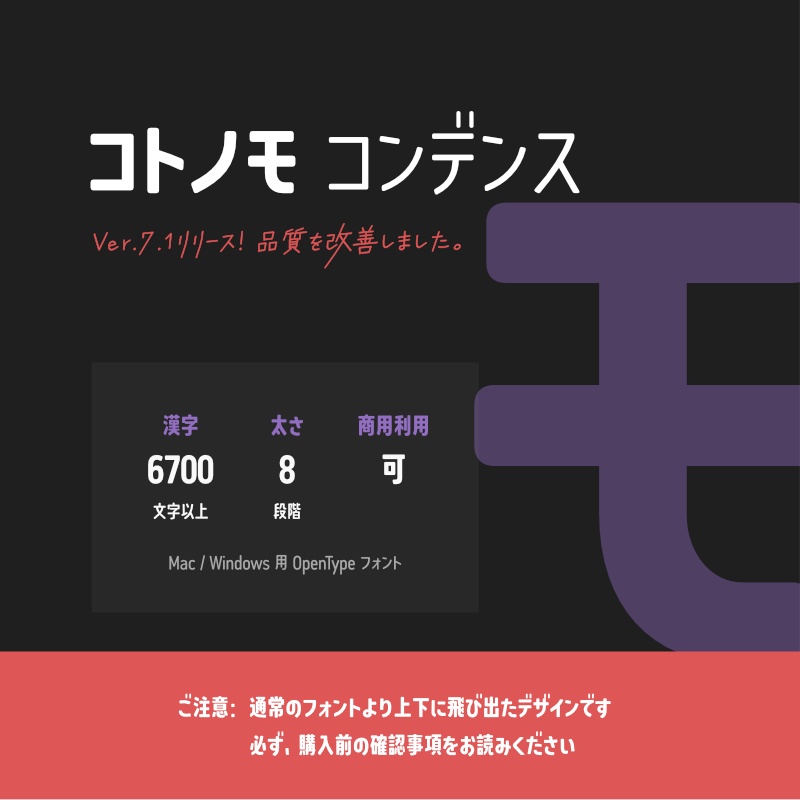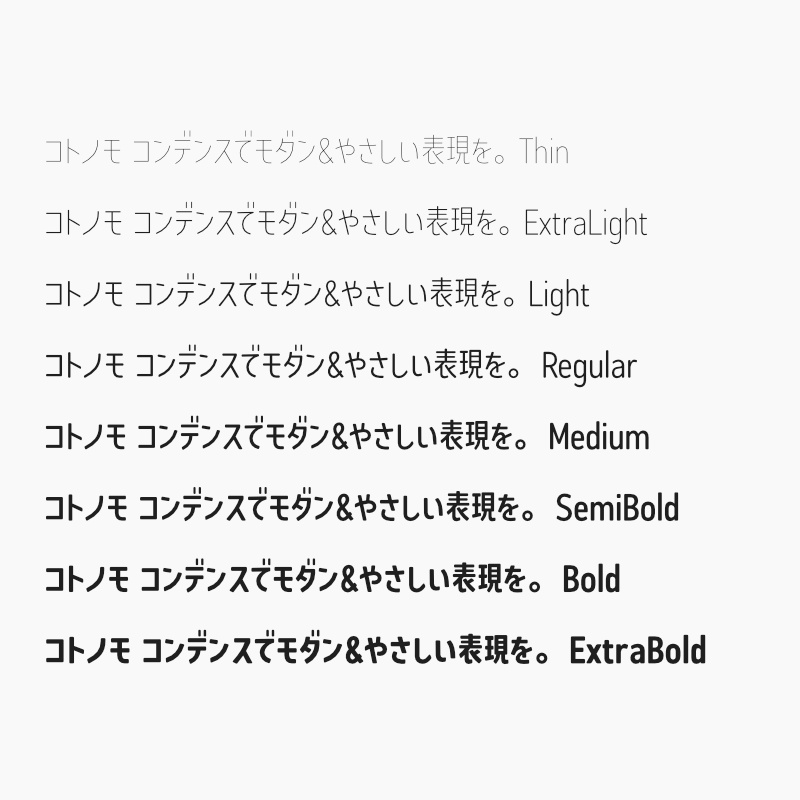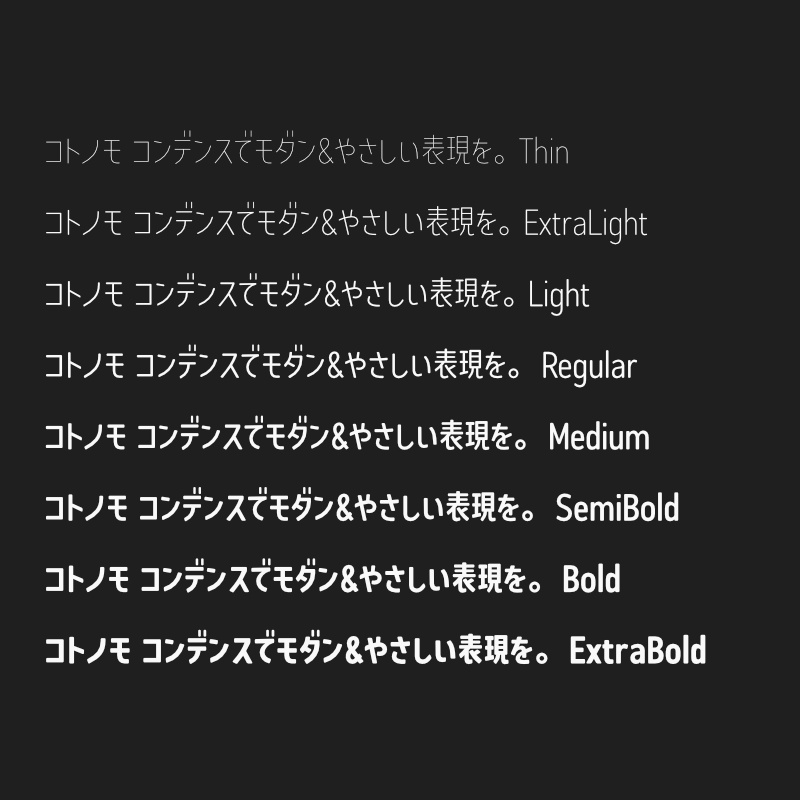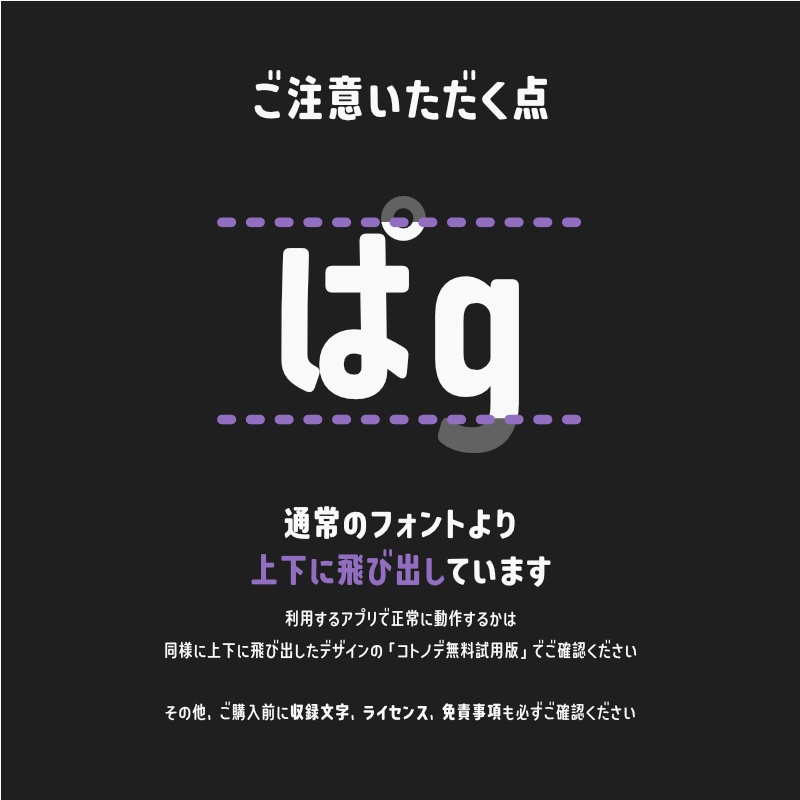
「コトノモ コンデンス」フォント(漢字あり) ~縦長で角丸のかわいい丸ゴシック体~
2024/09/30 ver.3.410 リリース。 2025/01/14 ver.3.600 リリース。一部の文字の表示崩れを修正しました。 2025/03/25 ver.4.105 リリース。濁点の位置を微調整しました。いくつかの文字のデザインを微調整しました。 2025/09/08 ver.4.106 リリース。一部カタカナのデザインを微調整しました。「以」「似」などを画数に忠実なデザインに変更しました。「篝」をJIS2004字形に変更しました。 2026/09/07 ver.7.103 リリース。「ð」「冕」2文字の誤字を修正しました。主に英数字において、曲線と直線の遷移をなめらかにしました。いくつかの文字(主に漢字)において、小さな凹みや欠片の除去を行いました。仮名文字の字間調整を行いました。その他いくつかの修正を加えました。その他、ウェイト差におけるデザインの一貫性向上、各ウェイトの太さの微調整(それに伴う横幅調整)なども行いました。 【ver.7.103へのアップデート時のご注意】文字幅変更を伴うアップデートです。旧バージョンのフォントファイルはバックアップを取り、フォントを更新した際は、成果物のレイアウトに崩れがないか必ずご確認ください。 【ver.7.103 更新内容(見本付き)】https://kotonohaworks.com/shiryou-pdf/update_kotonomo-n-sc-c_ver7-1.pdf ※購入済み商品の最新版は、「購入履歴」「ライブラリ」ページからダウンロードできます。